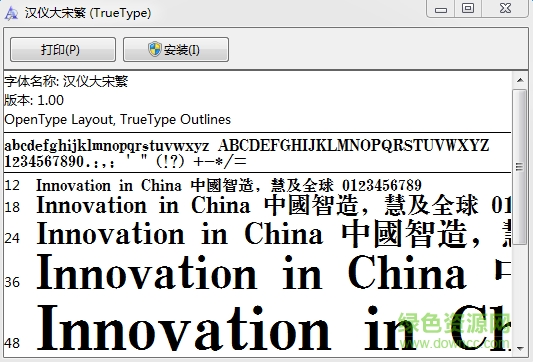
hya4gf是什么字體?hya4gf是漢儀大宋繁體字體,這款字體比一般的宋體字體要大得多,可用于正文標(biāo)題、包裝設(shè)計(jì)、雜志讀物等領(lǐng)域,需要的朋友快來(lái)下載使用吧!
漢儀字庫(kù)是中國(guó)大陸最早專業(yè)從事字形設(shè)計(jì)、字庫(kù)產(chǎn)品開發(fā)、漢字信息技術(shù)研究、漢字應(yīng)用解決方案的文化創(chuàng)意與信息技術(shù)企業(yè)。漢儀字庫(kù)擁有核心自主的知識(shí)產(chǎn)權(quán),為字庫(kù)用戶提供最豐富、全面、便捷、高效的字庫(kù)應(yīng)用解決方案!